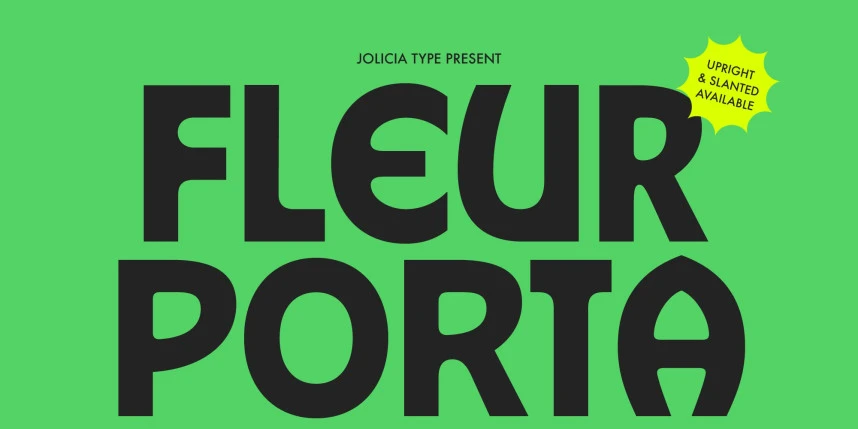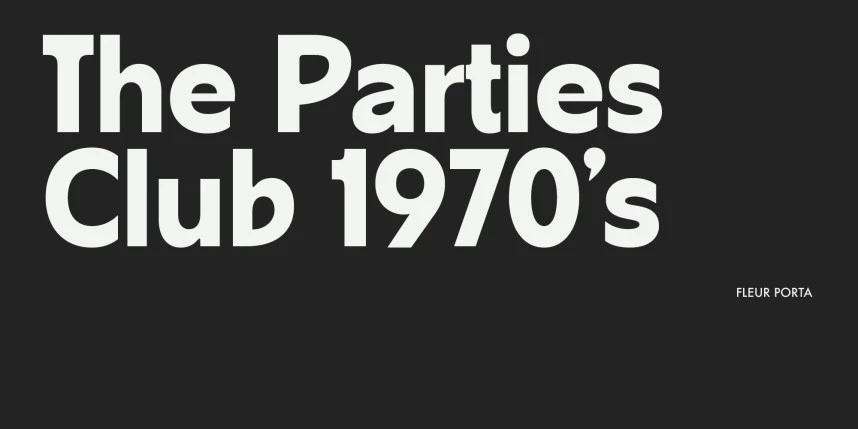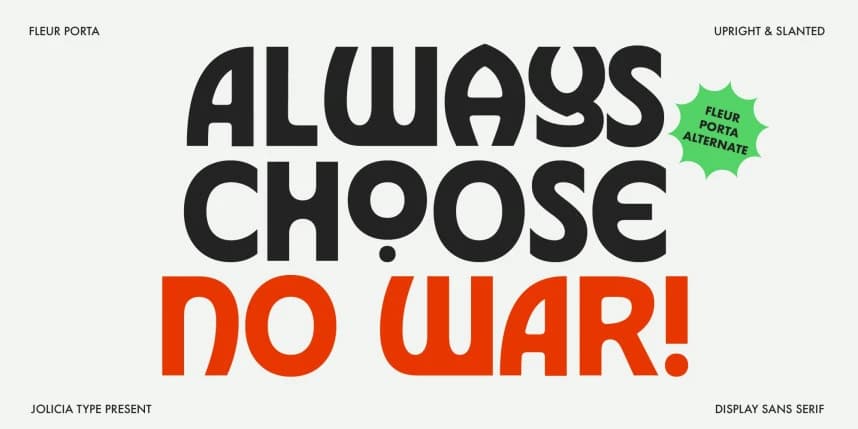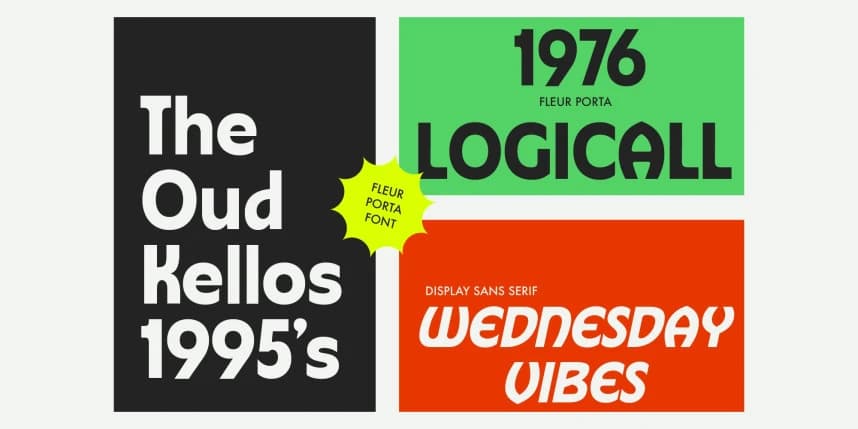
Fleur Porta Font
Fleur Porta Font, modern netliğiyle Art Deco zarafetinin ince bir dokunuşunu harmanlayan ayırt edici bir gösterişli sans serif tipografisidir. Öne çıkması için tasarlanan bu yazı tipi, temiz geometrik formları zarif dekoratif ayrıntılarla zenginleştirilmiş olarak sunar ve sadelik ile sofistike arası
Fleur Porta Font, modern netliği ile Art Deco zarafetinin ince bir dokunuşunu birleştiren ayırt edici bir gösterişli sans serif yazı tipidir. Dikkat çekmek üzere tasarlanan bu yazı tipi, temiz geometrik formları rafine dekoratif detaylarla zenginleştirilmiş olarak, basitlikle sofistikelik arasında mükemmel bir denge yaratır.